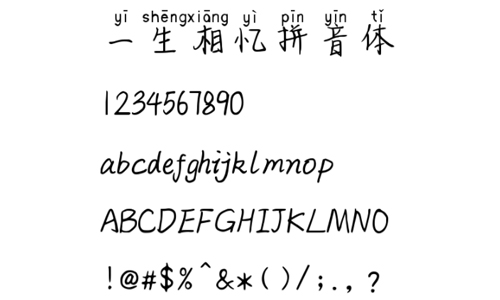
一生相憶拼音體字體是思雨字庫中一款自帶拼音音標(biāo)效果的手寫字體, 曾經(jīng)你是我最美麗的初戀,如今卻是我無法忘記的記憶,為何佛祖不能給我們那美麗的結(jié)局?卻讓我一生長相憶!——一生相憶拼音體。本字體是在國家標(biāo)準(zhǔn)簡體字庫GB2312所包含6763漢字的基礎(chǔ)上,又增加了近200常用字,已經(jīng)覆蓋了大陸99.75%的漢字使用頻率,足以滿足日常需求。歡迎大家前來下載。